表示できないテキストがあるとき代わりに表示される白い四角、これを無くすための戦いは古くから続けられていますが、それでもご覧になったことのある方は多いかと思います。この白い四角は見かけが似ているため「豆腐」と呼ばれることがあります。フォントによって違うデザインを設定できるので白い四角ではないこともあります。
AXIS Fontの場合「豆腐」は白抜きの四角にバツ印のデザインですが、開発中は立体的でしかもお皿まで付いてるアイコンで表示されることがあります。
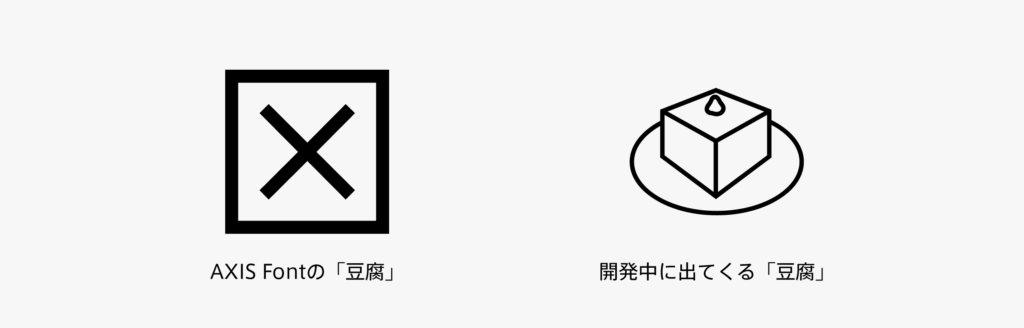
実は、先輩が「豆腐」と呼ぶまで私はこのアイコンを苺ショートケーキだと勘違いしていました。でもこれが豆腐で冷奴になっていると捉えるならば、上にちょこんと添えてあるのは苺ではなく生姜でしょうか。